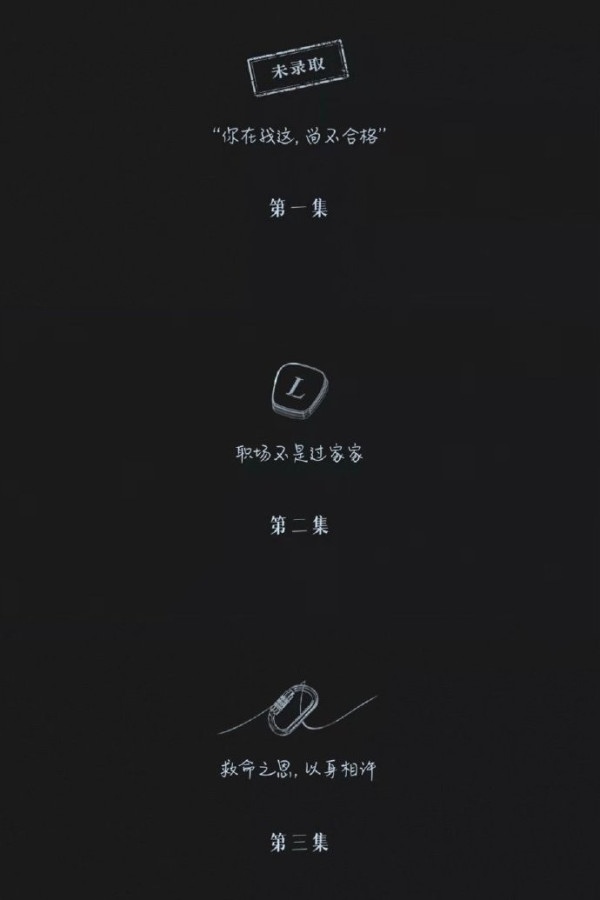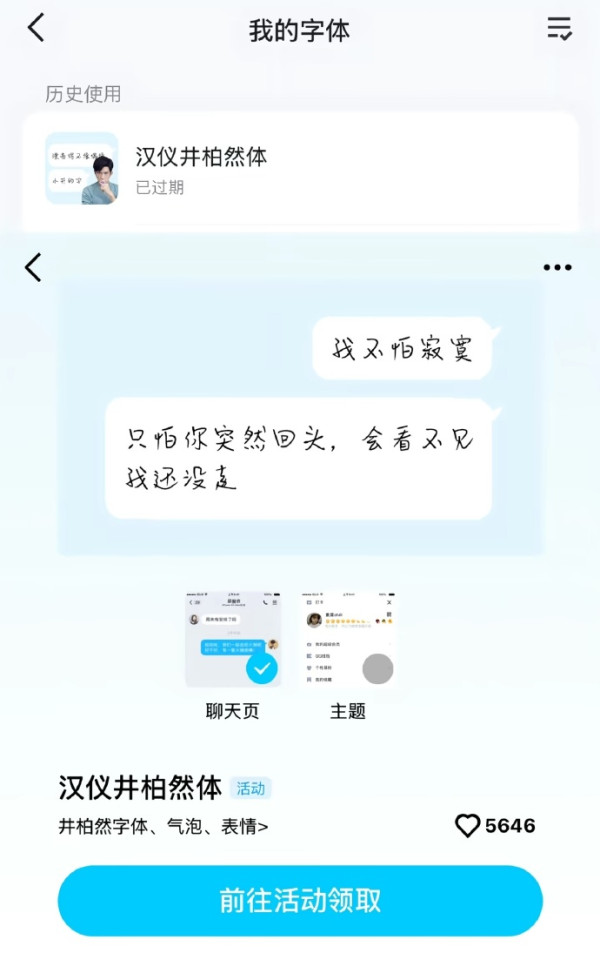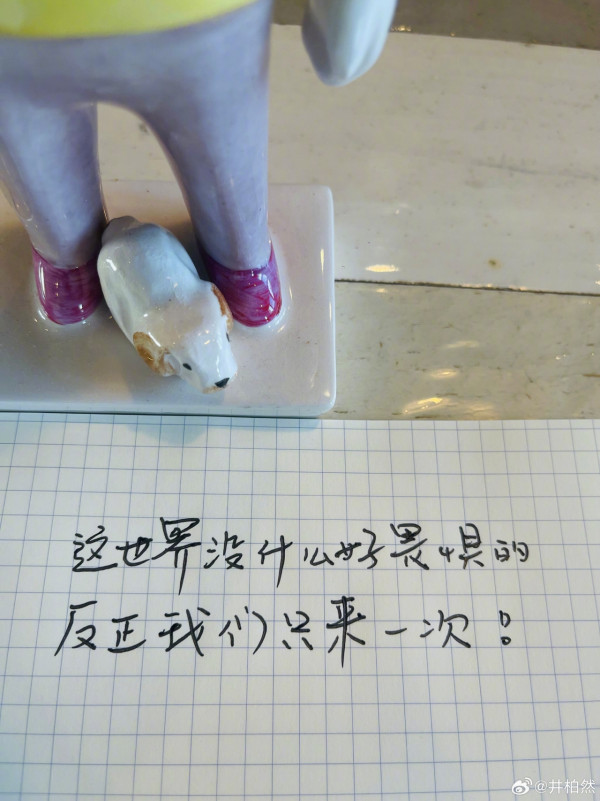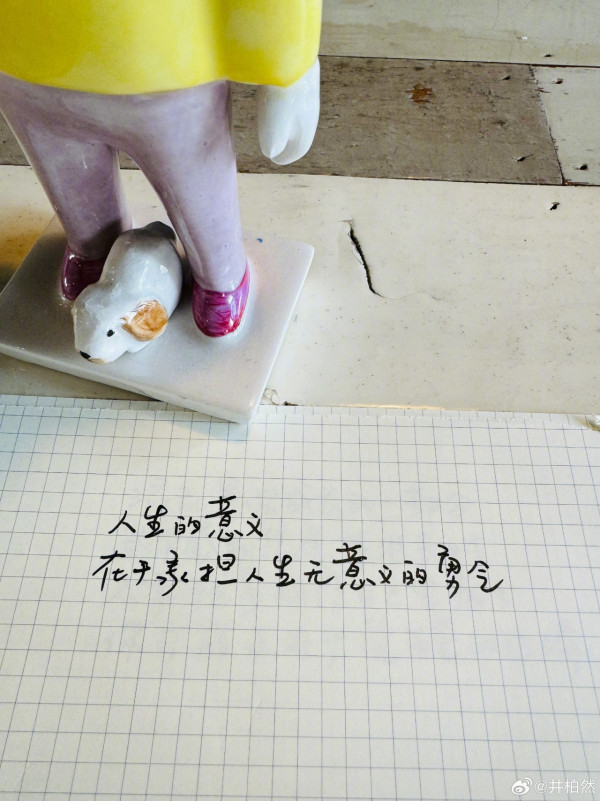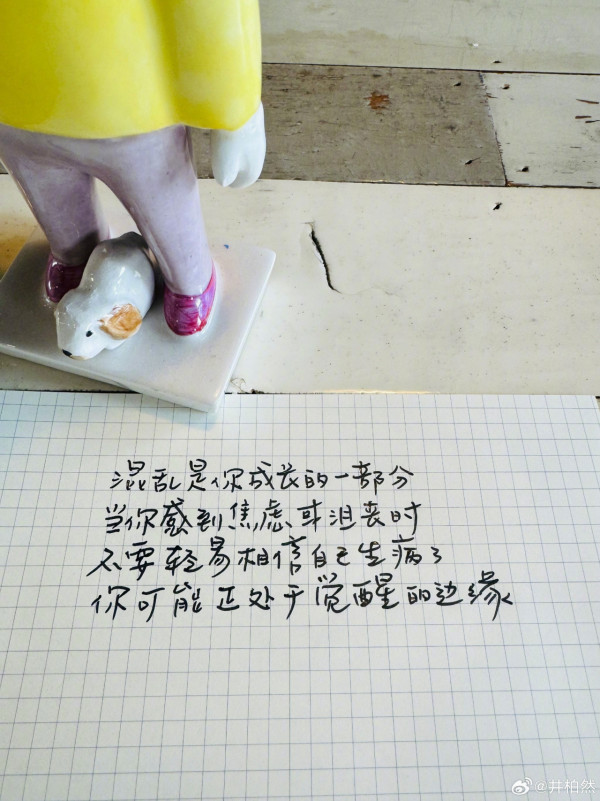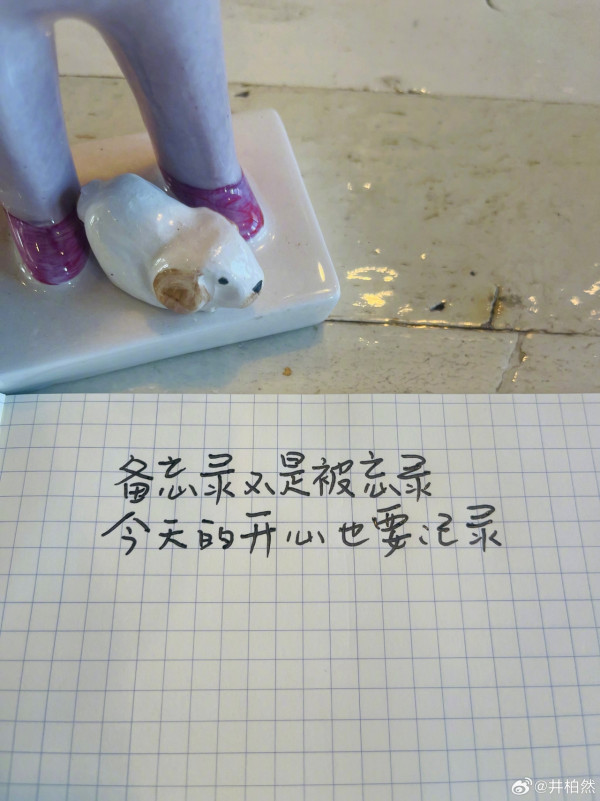
早春晴朗|井柏然手写标题传一字值千金!曾打造专属“井字体”早成招牌
国产剧《早春晴朗》开播后迅速掀起海内外追剧热潮,除了井柏然与孙千的办公室禁忌恋情备受瞩目,剧中每集片头的手写标题也成为观众热议的隐藏彩蛋。剧组证实,这些充满文艺气息的手写字体,全都是出自井柏然本人之手,而他的字迹早已因“一字值千金”的惊人身价成为业界佳话。
《早春晴朗》井柏然亲笔手写每集标题
《早春晴朗》官方微博正式发文证实,剧中每集片头出现的标题字体,并非剧组另外委托书法家设计,而是由男主角井柏然亲笔完成。从第一集的“未录取:你在我这,尚不合格”、第二集的“职场不是过家家”,到第三集的“救命之恩,以身相许”、第四集的“跟我回家”,这些充满个人风格的标题,皆出自井柏然之手。他的字迹并非传统工整的楷书,而是带着随意与洒脱,笔画间流露出一种独特的清新与温度,完美契合了剧集的都市文艺氛围,让观众直呼“连字看着都赏心悦目”。
消息曝光后,不少熟悉井柏然字迹的粉丝立即留言表示“早就从笔迹认出偶像”,并大赞字体“可可爱爱又有辨识度”,这种极具个人特色的“井字”,也让剧集在正片内容之外,多了一层让粉丝会心一笑的细节彩蛋。
井柏然主动提议 反复打磨17版手稿
据剧组透露,这个手写标题的构思并非剧方要求,而是井柏然在剧本围读阶段就主动提议,希望能够亲手为这部作品题写每集标题。为了让字体风格完美贴合剧集的都市成人氛围与情绪节奏,他前后反复调整、打磨了整整17版手稿,才最终定案。这份对细节近乎苛求的坚持,也让不少观众直呼“湛念(剧中角色)太有才了”,并肯定他对整部作品品质的用心程度,不仅仅止于表演本身,更延伸到剧集视觉呈现的每一个环节。
他时不时都喜爱在社交平台分享一些自己手绘和手写的字句画作,在上部主演剧时他也分享过一张分析女主角周乔(蔡文静饰)的内心思想,与粉丝可爱互动的一种方式。
井柏然向来一手好字 打造专属“井字体”
其实井柏然的好字并非因《早春晴朗》才被发现,而是早就是他多年来的个人招牌。他的字迹最早在2015年参与实境节目《花儿与少年第二季》时被观众注意到——当时他负责撰写旅行日记,清秀又极具辨识度的笔触迅速在网络上引发讨论,不少粉丝直呼“原来偶像的字这么美”。他平日也时不时喜爱在微博分享手写金句,勉励粉丝,以及分享一些人生的想法。
同年,他更进一步将这份才气化为正式作品,与汉仪字库合作,亲手写下3000个常用中文字,打造出专属的“汉仪井柏然体”,并于2015年9月21日正式在手机QQ字体商城上线。这让井柏然成为中国新生代男演员中,首位拥有专属电脑字体、正式“字体入库”的艺人,粉丝从此可以将偶像的亲笔笔迹,直接变成手机上日常使用的字型,这在当年的娱乐圈堪称独树一格的创举。
剧中每集片头的手写标题均出自男主角井柏然之手,他亲笔完成了这些充满文艺气息的字体,完美契合剧集氛围。
井柏然的好字早在2015年参与《花儿与少年第二季》时就被观众注意到,他更与汉仪字库合作推出“汉仪井柏然体”。